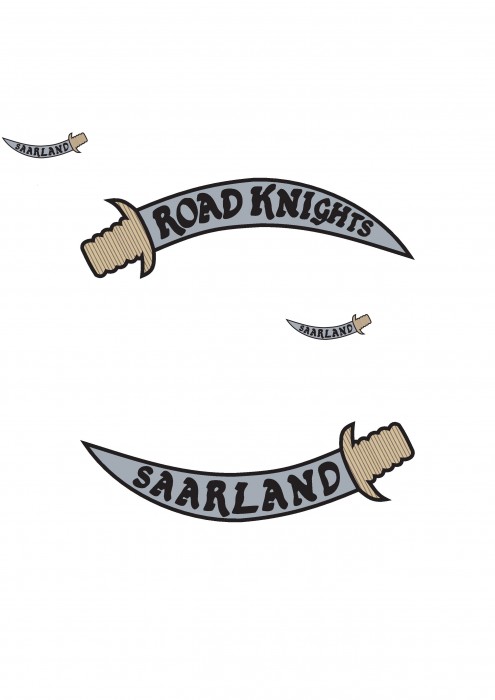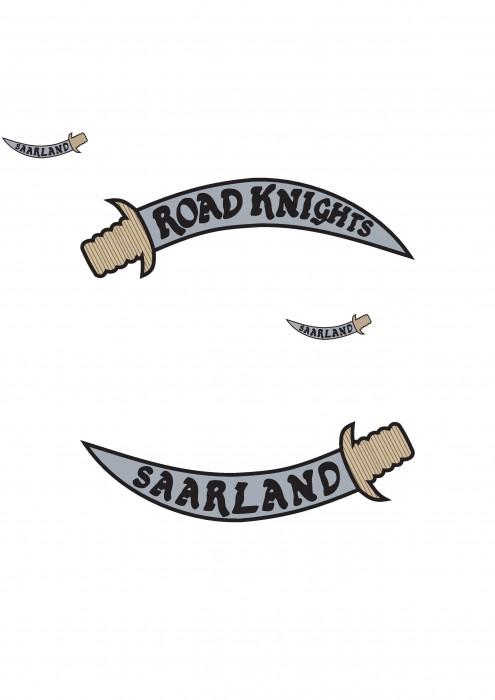
Schrift aus Club Color gesucht MC ROAD KNIGHTS WARNDT
ich suche einen Schriftartensatz mit dem ich das Color des MC ROAD KNIGHTS WARNDT
nachsticken lassen kann.
Der Club hat seinen Sitz im Saarland und die Schrift wird seit 1986 verwendet.
Habe mehrere Fotos der Schriftart aber keine Quellen mehr.
Die Fotos stammen teilweise aus 1986 und 2005
das sollte doch eigentlich auch mit den Bildern gehen oder nicht?!
Oder willst du das Saarland durch Warndt ersetzen? Dann muss man wohl das W aus der ersten Datei nachbauen oder ein neues W entsprechend erfinden und den Rest aus den vorhandenen Zeichen nachbauen.
Eine Schrift wirst du wahrscheinlich nicht finden, das wird irgendwer mal so gezeichnet haben.
Nicht, dass ich die Schrift schön finde, aber die Colors sind nunmal so – da kommt dann auch keine ähnliche Ersatzschrift in Frage ...
Ich habe auch nochmal geguckt, leider habe ich auch nur die Schwerter und den Geier in der Mitte als Vektorzeichnung.
Ja das dachte ich auch schon. Wäre halt schön gewesen wenn es den Schriftsatz geben würde. Dann muss ich mir die Arbeit machen und was "malen"
Es handelt sich hier offensichtlich um eine sehr schlecht gezeichnete "Capitalis Rustica".
Gibts auf diversen Free-Font-Seiten in wesentlich besserer Qualität.
Passt leider so gar nicht! Ich denke dass es eine Kalligrafie ist! Muss man wohl nachzeichnen.
Kalligrafie würde ich es nicht nennen, aber handgezeichnet ...  8-)
Passt leider so gar nicht! Ich denke dass es eine Kalligrafie ist! Muss man wohl nachzeichnen.
Dass die Vorlage so anders aussieht als eine echte Rustica ist nicht zu übersehen.
Wollte dir nur zeigen, welche Schrift der Schöpfer dieses „Werks“ nachahmen wollte.
Und dachte eben, dass dir das auffällt.